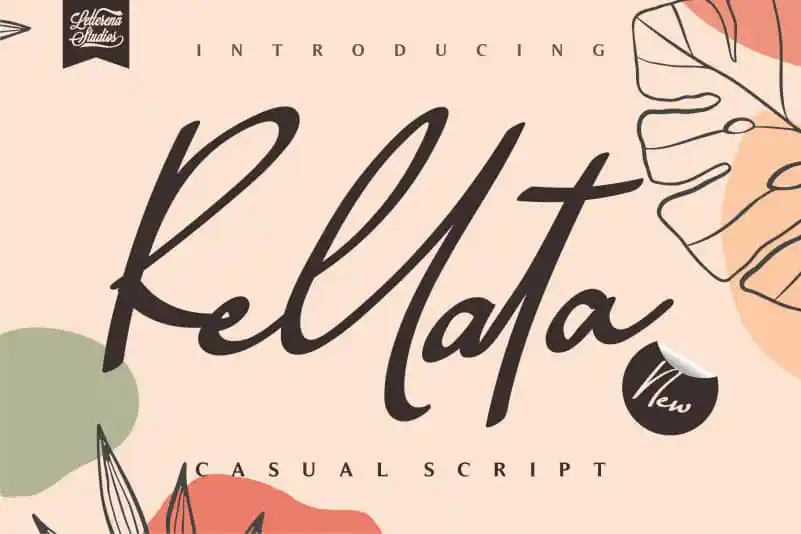
A Rellata Script Font é uma elegante escolha para projetos que precisam de um toque romântico e delicado. Com seu traçado fluido e detalhes charmosos, essa fonte tem a capacidade única de enriquecer qualquer projeto, seja ele para identidades visuais, mensagens expressivas ou até mesmo elementos decorativos como capas de livros, cartões de nome, convites e muito mais. As obras da letterenastudios não ficam apenas nas bordas dos seus projetos; elas estão dentro delas, criando um ar delicado e sofisticado que eleva qualquer design para o próximo nível. Seja qual seja o seu projeto, a Rellata Script Font traz uma sensação de elegância e delicadeza que fará com que sua marca brilhe ainda mais.